1、制定一个设计基调:
对作品而言,每一件作品都有其特有的风格。在这个前提下,一个作品版面上的各种不同字体的组合,一定要具有一种符合整个作品风格的风格倾向,形成总体的情调和感情倾向,不能各种文字自成一种风格,各行其是。总的基调应该是整体上的协调和局部的对比,于统一之中又具有灵动的变化,从而具有对比和谐的效果。
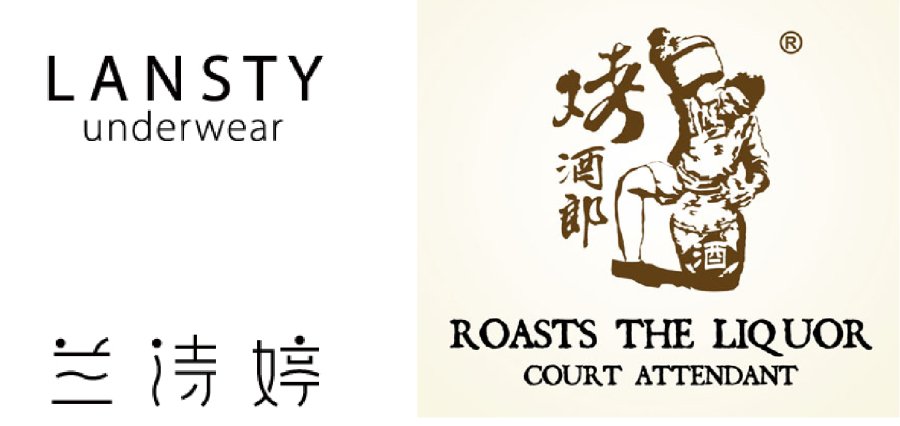
2、注意字体的外形特征
不同的字体具有不同的视觉动向,例如:扁体字有左右流动的动感,长体字有上下流动的感觉,斜字有向前或向斜流动的动感。因此在组合时,要充分考虑不同的字体视觉动向上的差异,而进行不同的组合处理。合理运用文字的视觉动向,有利于突出设计的主题,引导观众的视线按主次轻重流动。
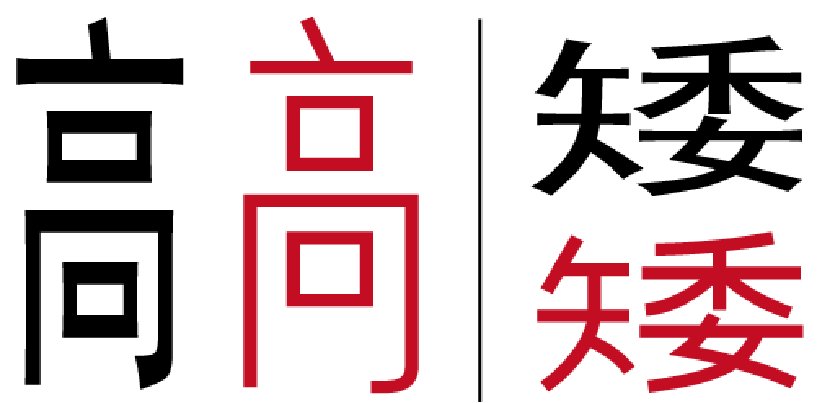
3、阅读习惯的影响:
水平方向上,人们的视线一般是从左向右流动;垂直方向时,视线一般是从上向下流动;大于45度斜度时,视线是从上而下的;小于45度时,视线是从下向上流动的。